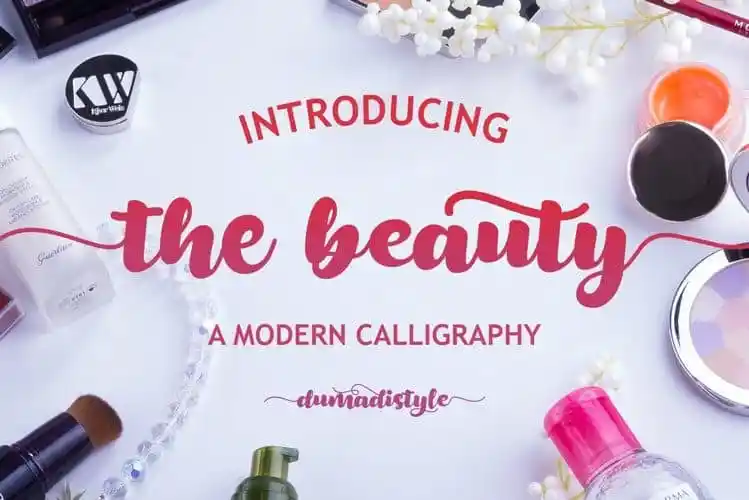
The Beauty Script Font – Download Grátis
A fonte ‘The Beauty Script’ é uma opção ideal para quem deseja adicionar um toque elegante e profissional a projetos que necessitam de personalidade, como criações relacionadas ao bem-estar pessoal ou à marca. Este script moderno foi pensado para aquelas pessoas que desejam aplicar seu bom gosto na área da beleza, skincare, logos ou qualquer outro tipo de branding. A fonte ‘The Beauty Script’ é uma coleção de fontes feitas pela designer DUMADI e ela oferece ligaturas incríveis, padrões naturais e um fluxo fluido, tudo sem esforço do usuário. Seu uso permite que você crie letra à mão com facilidade, tornando-o perfeito para projetos em que a delicadeza e o cuidado são fundamentais, como os produtos de beleza ou logos de marcas. Com ‘The Beauty Script’, as ideias ficam ainda mais brilhantes e seu design personalizado estará sempre impecável.